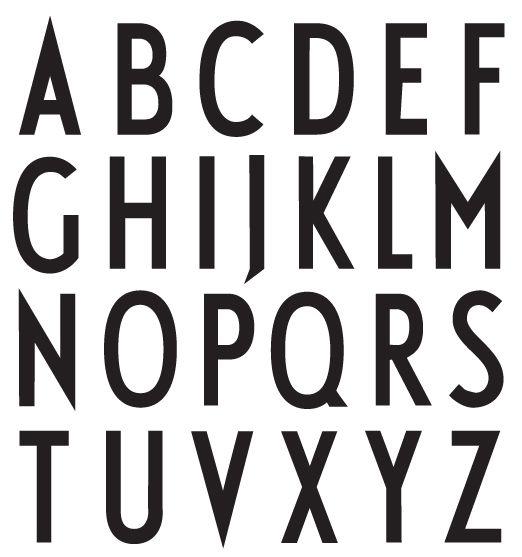
Schrift "Design Letters" gesucht! (Aarhus City Hall)
Ich bin auf der Suche nach einer Font, die der des Labels Design Letters sehr, sehr ähnlich sieht, bzw nahezu identisch ist.
Die Original Schrift ist von Arne Jacobsen, hat keinen Namen und ist nirgends erhältlich.
Zumindest die Spitzen sind spitz …
Aber zur Schrift: Ich hab da mal eine Express-Fonterisierung gebaut :-)